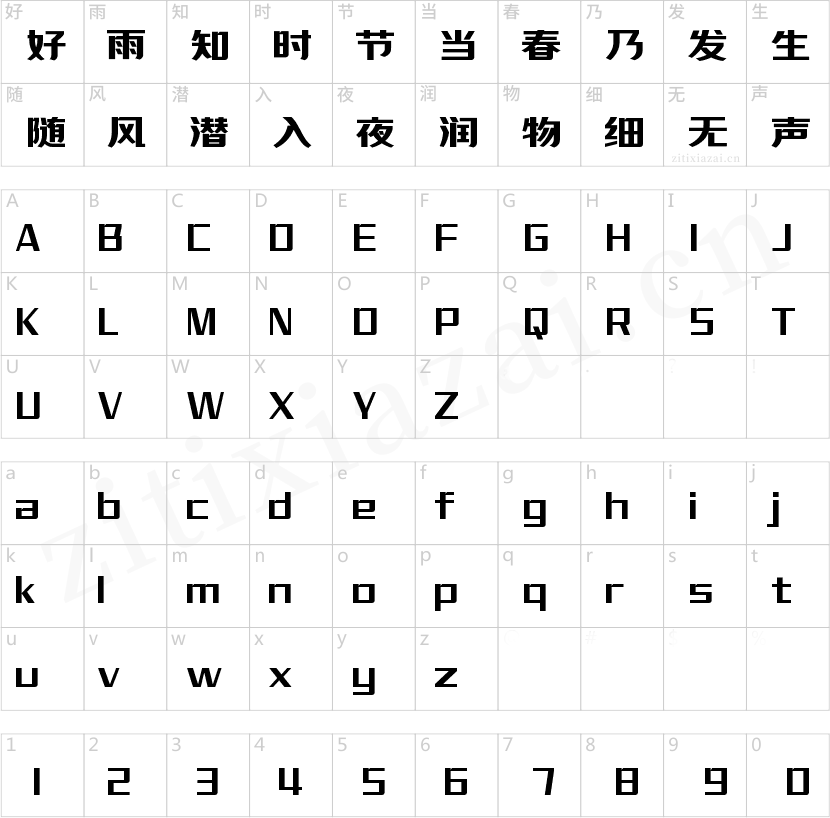
壹心摩卡黑
壹心摩卡黑,这款字体结构工整、笔画清晰,兼顾美观与易读性,适用于标题、正文、海报、包装、LOGO 等多种场景。字形优雅稳定,风格百搭耐看,适配日常排版与创意设计,让文字呈现更舒适、更具质感。壹心摩卡黑一笔一画,皆是细节,以均衡的比例、流畅的线条打造舒适视觉体验,字形端正大气,风格简约现代。无论是商业设计、品牌宣传还是日常排版,都能轻松驾驭,让文字更有格调与力量。壹心摩卡黑字体下载。